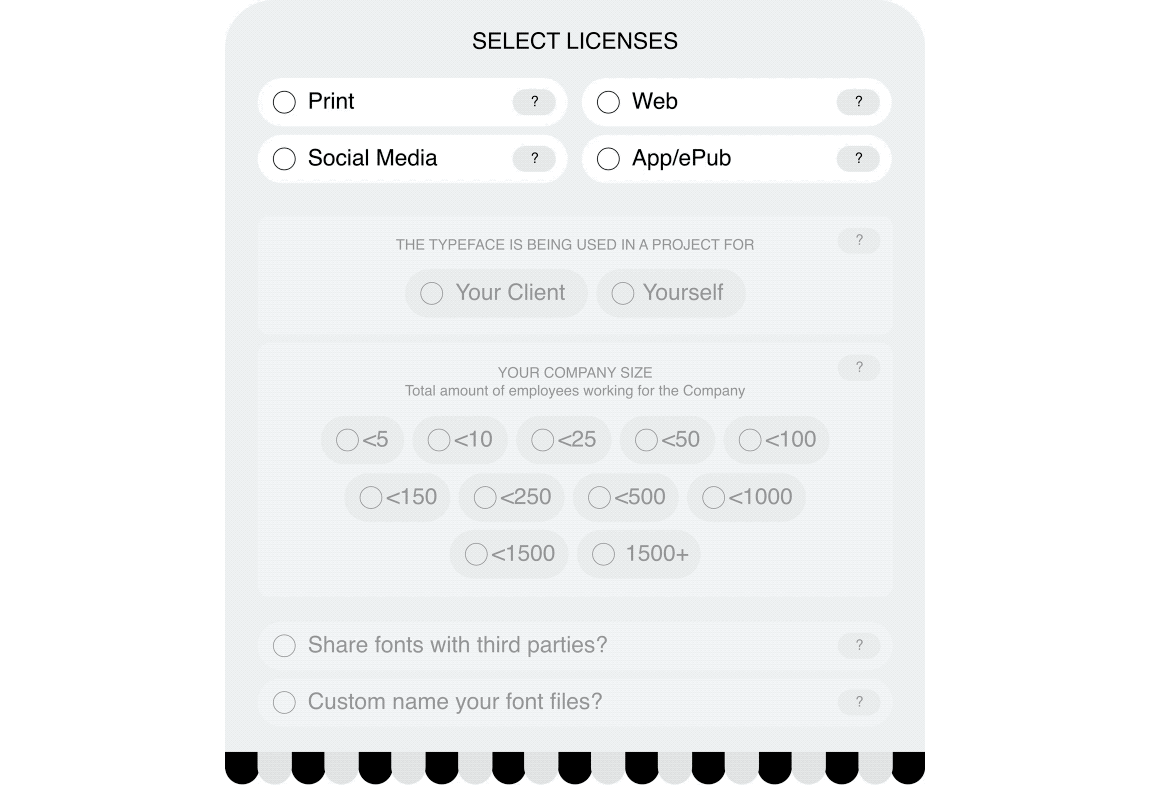
Je hebt typefoundries die hun lettertypes in de spotlight zetten en zelf op de achtergrond blijven, en je hebt typefoundries die evenveel karakter in hun characters steken als in hun eigen branding. Het Zwitserse Dinamo valt definitely in de tweede categorie.
Ze maken niet alleen ruige typefaces (zoals de klassieker Favorit), maar vernieuwen ook op het gebied van variable fonts, trial fonts, tutorials, AR face masks, hardware goodies en een website vol gekkigheid. Hun nieuwste innovatie: font licenties.
Doorgaans is de prijs van een lettertype gebaseerd op het aantal computers waarop het geïnstalleerd wordt. Dat kan betekenen dat bijv. een groot autobedrijf met een kleine ontwerpafdeling minder betaalt dan een culturele instelling waar veel medewerkers met het lettertype werken. Dinamo vindt dat unfair en neemt nu afscheid van het usage based model en introduceert een value based model.
De prijs van een lettertype wordt niet meer gebaseerd op hoeveel medewerkers met het font gaan werken, maar op het totaal aantal medewerkers van het bedrijf. Dat geldt ook voor webversies: het aantal maandelijkse pageviews maakt niet meer uit; alleen bedrijfsgrootte telt. En dat is goed nieuws voor freelancers, kleine ontwerpstudio's en culturele instellingen.
Hopelijk volgen andere typefoundries dit voorbeeld!
🔥 Design System fetisjist? Dan is deze enorme videocollectie voor jou. — www.designsystemtalks.com
🔥 Deze guy tweakte een Snap lens waardoor in video calls z'n gestures worden ondersteund door teksten in comic-book style. — twitter.com
🔥 Ein-de-lijk ondersteunt Sketch color swatches. Dus een kleur op één plek wijzigen en hij wordt in het hele document aangepast. — www.sketch.com
🔥 Een massieve video cursus visual interface design, door Matt D. Smith. — shiftnudge.com
🔥 Dit wayfinding systeem voor de Nationale Bibliotheek in Luxemburg is een heerlijk gevalletje 'mooi maar onbruikbaar'. — kottke.org
🔥 Microcopy is een krachtig wapen als je weet hoe het wapen werkt. Product designer Anthony Diké geeft 40 pro tips. — twitter.com
MUST: LUUK VAN DE VEN
Luuk ontwerpt merken vanuit Amsterdam Noord.
Must read
Font Review Journal – Ontwerpster Bethany Heck schrijft mooie, uitgebreide reviews van nieuwe font releases. Ze beoordeelt ook klassiekers als Windsor en Cooper. Met heel veel beeldmateriaal en details!
Must see
De Insta van OH no Type Co – Een van de leukste én leerzaamste typografie Instagram accounts is voor mij die van OH no Type Co. Afgelopen zomer liepen ze letter voor letter door het alfabet en nu posten ze een paar keer per week algemene tips voor het ontwerpen van letters (vectorising, licensing, spacing etc.).